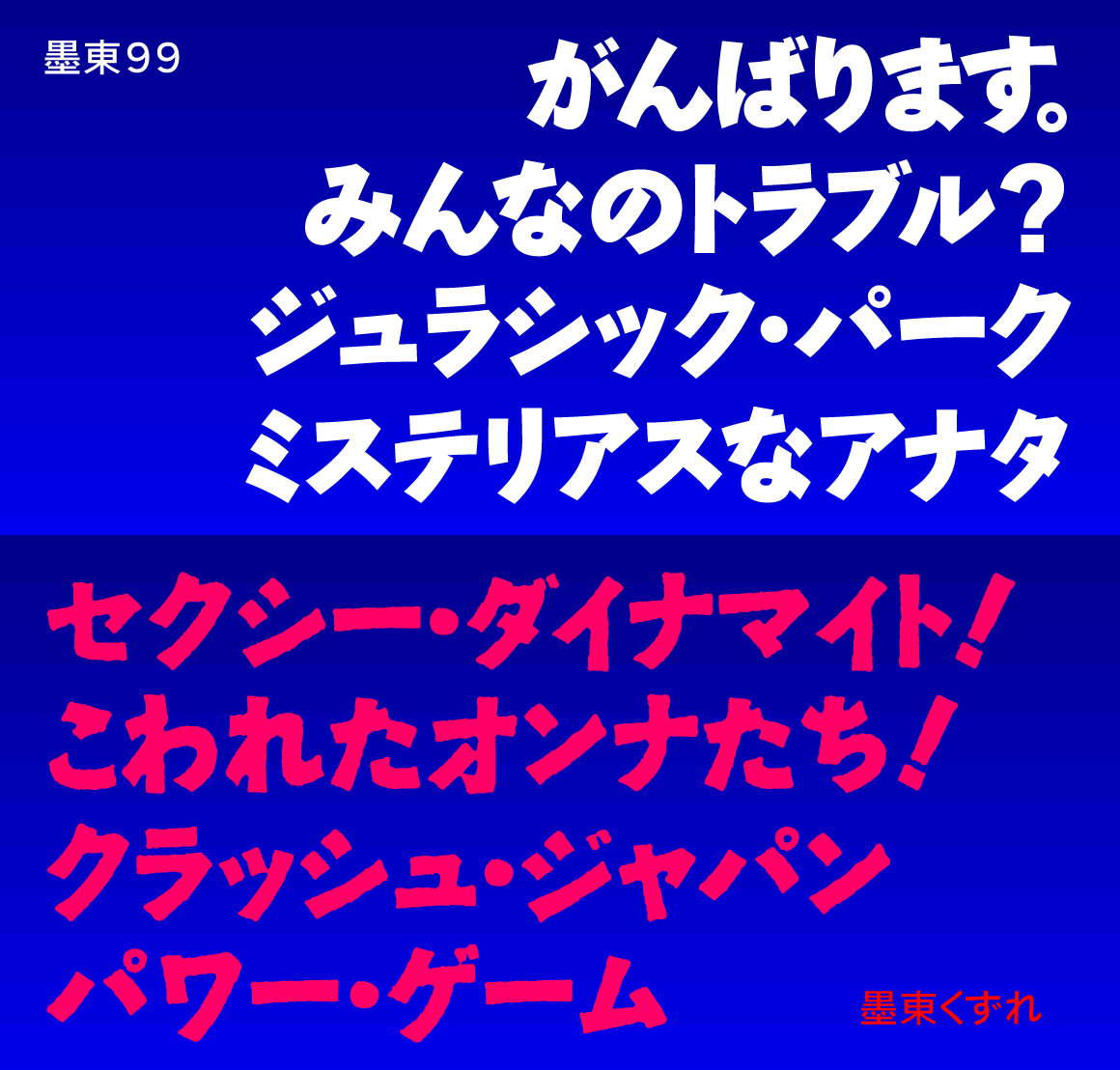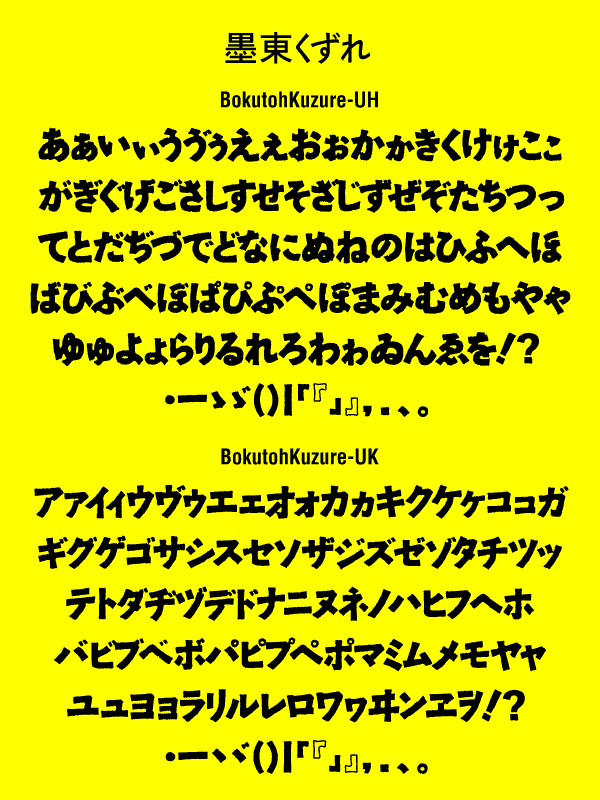
墨東99(無料頒布、かな1バイト) 2008.08.01 |
| Bokutoh99-UH(ひらがな) Bokutoh99-UK(カタカナ) |
| 墨東くずれ(無料頒布、かな1バイト) 2001.07.30 | |
| BokutohKuzure-UH(ひらがな) BokutohKuzure-UK(カタカナ) |
| デザイン |
墨東かな書体は、かな文字本来の骨格を生かしながら、美しく肉付けした角ゴシック書体です。 一番太いものが「墨東99」。その墨東99の輪郭線をガタガタにくずして、迫力と味わいを加えたものが「墨東くずれ」です。 ウソのない直球勝負のタイトルなどに最適だと思います。 |
ゴツイ・強そうで日本男児っぽい・ダイナミック・男らしい・パンチがある・インパクトがある・骨太な感じ・かっこいい・文字に力がある・見やすくバランスが良い・本格っぽい・パワフル・ドラマチック・スゴク目を引く…。 |